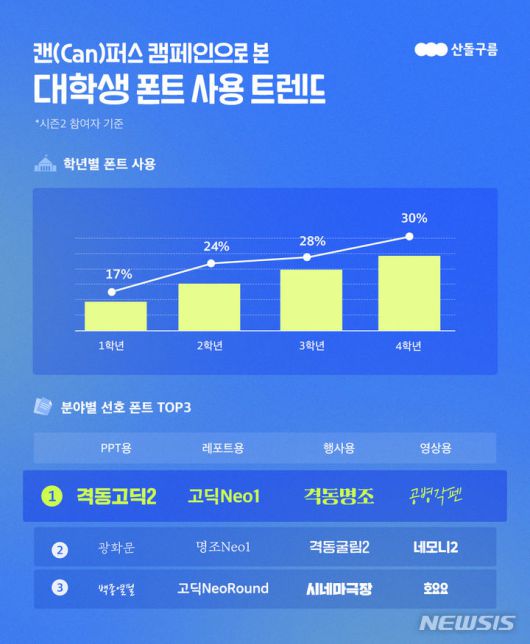
[서울=뉴시스]이수정 기자 = 산돌은 자사 폰트 플랫폼 산돌구름에서 실시한 '산돌구름 캔(Can)퍼스 캠페인 시즌2'의 운영 결과, 대학 고학년일수록 폰트 사용 선호도가 높게 나타났다고 28일 밝혔다.
산돌구름 캔퍼스 캠페인 시즌2는 대학생을 대상으로 학업에 필요한 폰트와 템플릿 및 대학생활 꿀팁 등을 무료 제공하는 캠페인으로 지난 2월부터 6월 말까지 실시됐다. 이번 시즌에는 전국 대학교 중 약 72%가 참여한 것으로 집계됐다.
이중 학년별 참여 비율을 살펴봤을 때 가장 높은 비율을 차지하는 것은 대학교 4학년으로, 전체의 30%를 차지하는 것으로 나타났다. 뒤를 이어 ▲3학년, 28%▲2학년, 24% ▲1학년, 17% ▲4학년 초과학년, 1% 순이었다.
이는 대외활동, 취업 준비, 졸업준비회 등 학년이 올라올수록 폰트 사용이 더욱 필요해지기 때문으로 분석된다.
또 학과별 신청 현황을 살펴보면 디자인 관련 학과의 경우 39%, 디자인 비관련학과에서 61%가 신청한 것으로 조사됐다. 폰트 사용 목적별 선택 비율을 살펴본 결과, 평균 사용 비율은 ▲레포트용, 30% ▲PPT용, 29% ▲행사용, 25% ▲영상용, 24%로 고르게 나타났다.
가장 선호되는 폰트는 사용처별로 선호 양상이 뚜렷했다. PPT용으로는 개성 강한 제목용 폰트 'Sandoll 격동고딕2'이 인기가 있었고, 레포트용으로는 높은 가독성의 'Sandoll 고딕·명조Neo' 시리즈 등이 많이 이용됐다.
영상 제작시 주로 사용된 폰트는 손글씨 폰트로 친근한 느낌을 주는 'Sandoll 공병각펜'이었으며, 행사용 폰트로는 레트로한 느낌을 주는 'Sandoll 격동명조'가 많이 사용됐다.